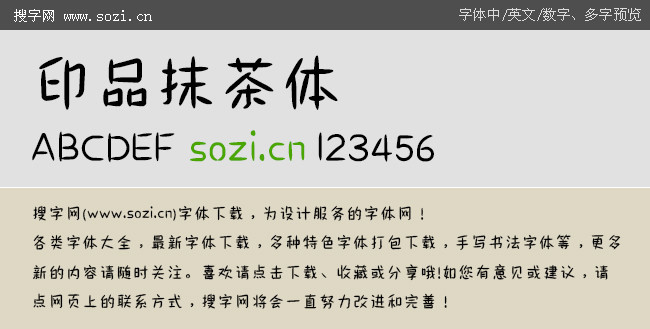
印品抹茶體
搜字網(wǎng)給大家提供一款印品抹茶體中文字體下載,該字體結(jié)構(gòu)端秀清新,一筆一劃飄逸瀟灑,仿佛是由無(wú)數(shù)片嫩葉組合而成,給人生機(jī)勃勃的感覺,每一筆都是個(gè)體,形疏而氣緊。適用于海報(bào)設(shè)計(jì)、包裝設(shè)計(jì)、商業(yè)廣告等廣告設(shè)計(jì)。